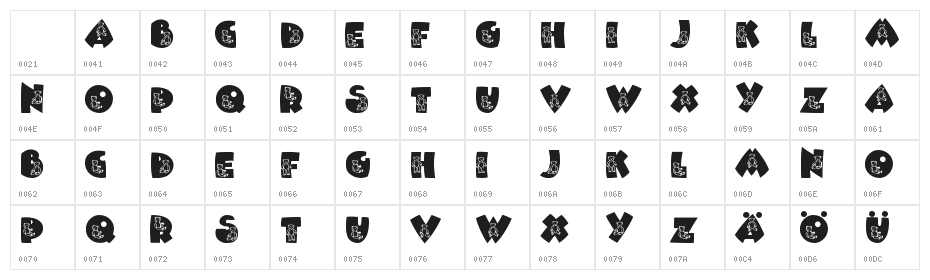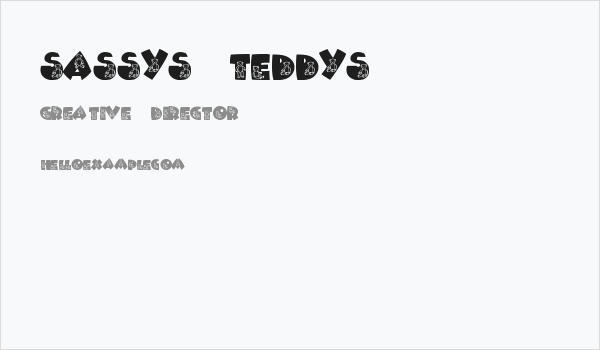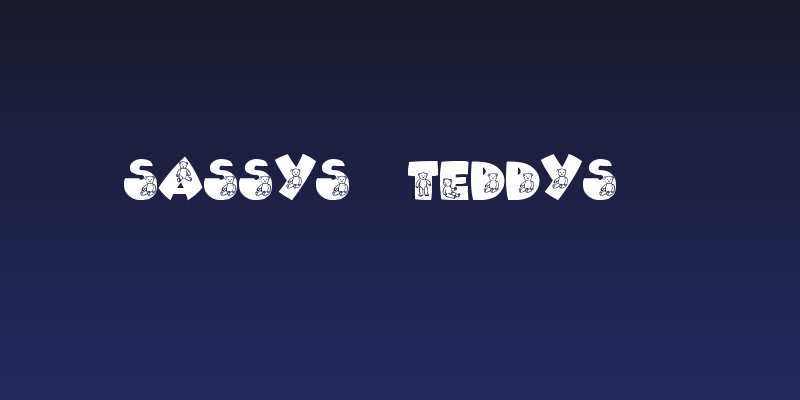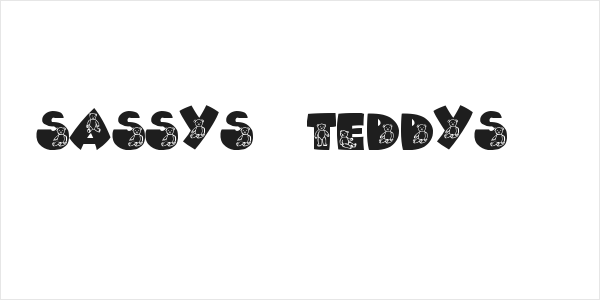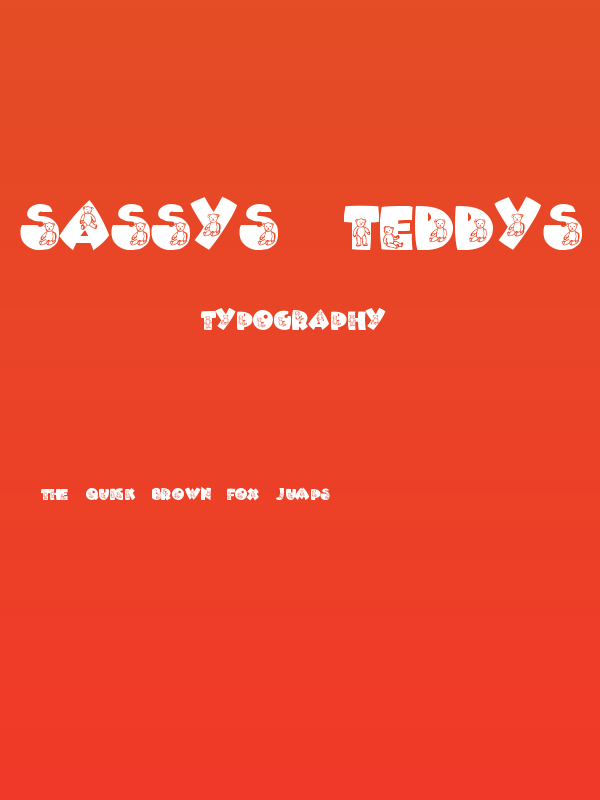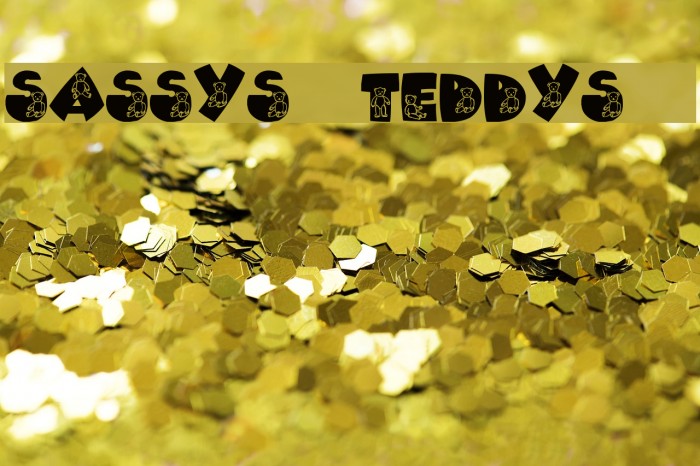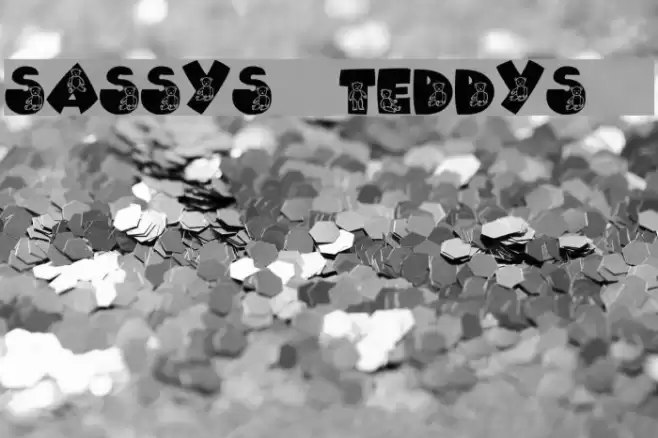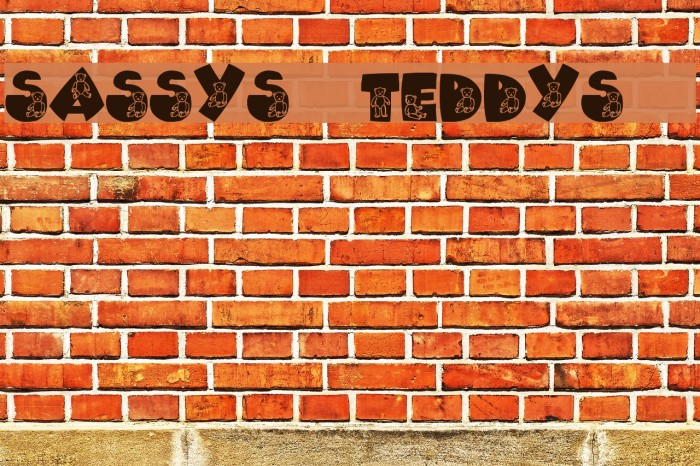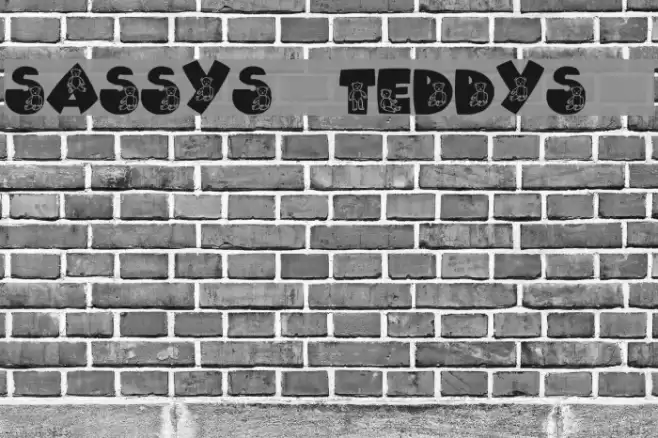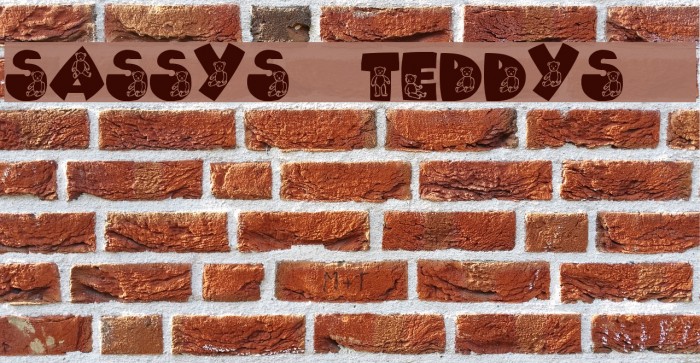
Sassys Teddys 2 Font
| Kategorien | Decorative |
| Gesamtstil | Playful, Whimsical |
| Vorgeschlagene Projekte | Ideal for children's books, playful branding, party invitations, and educational materials. |